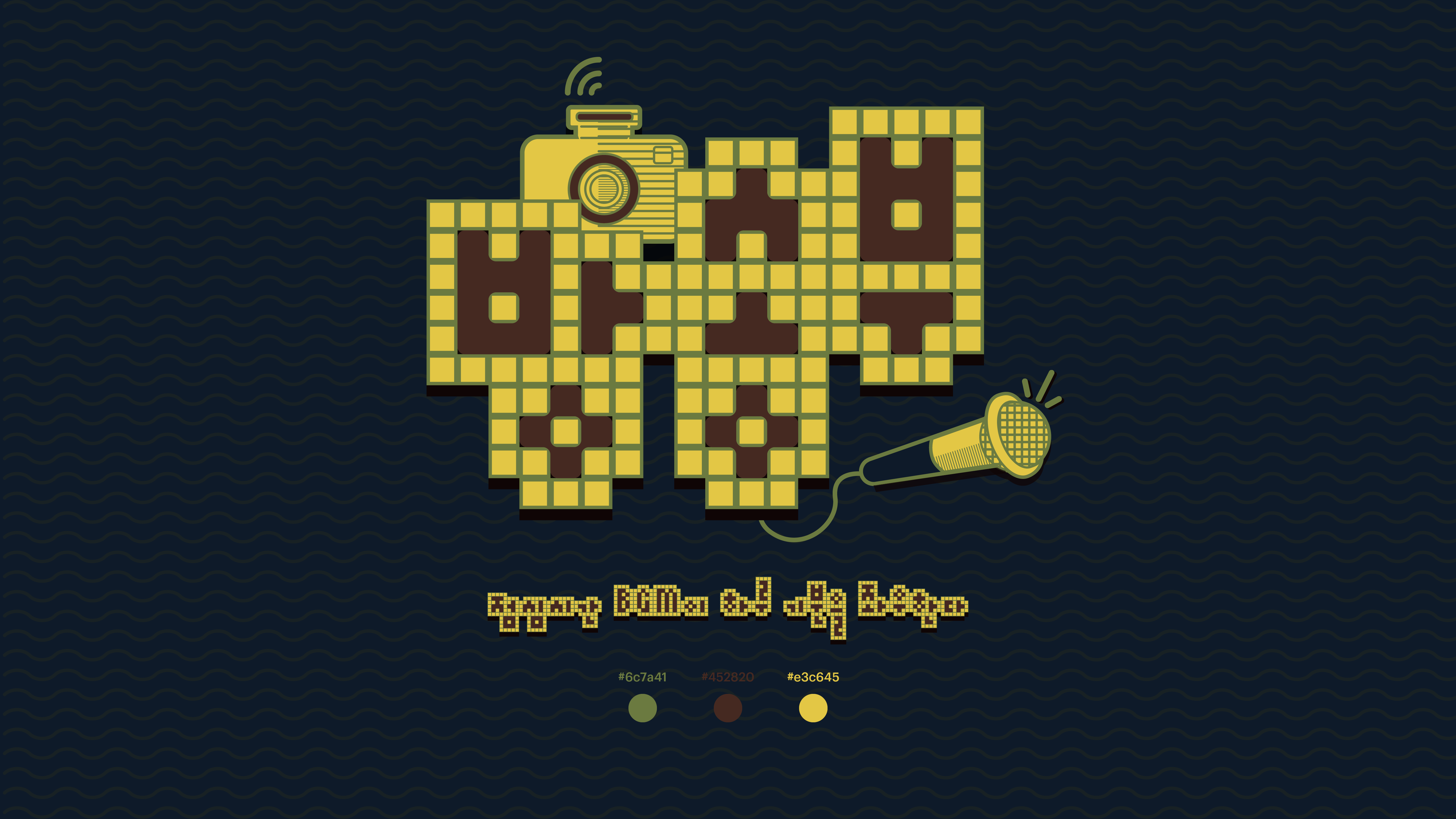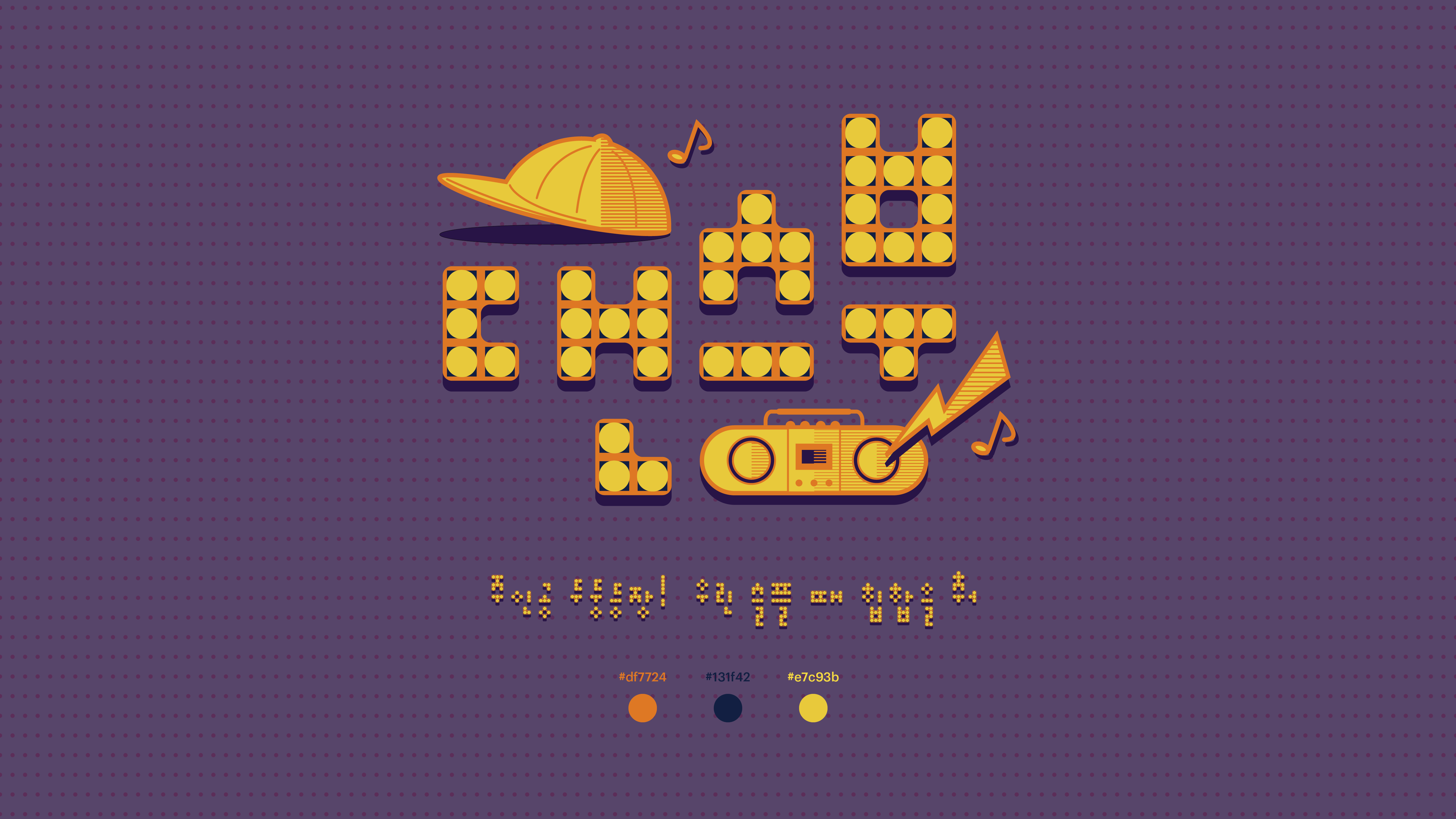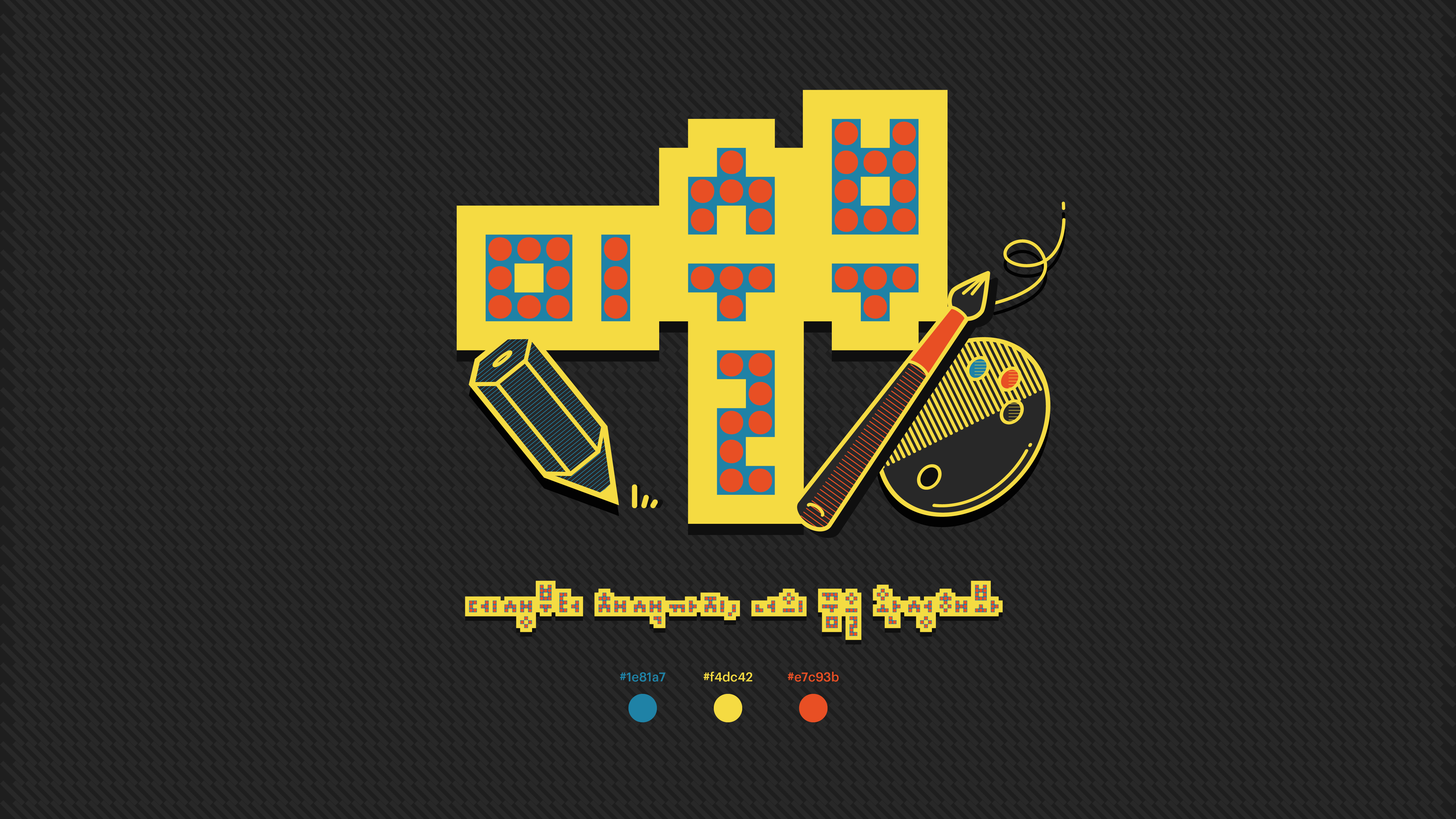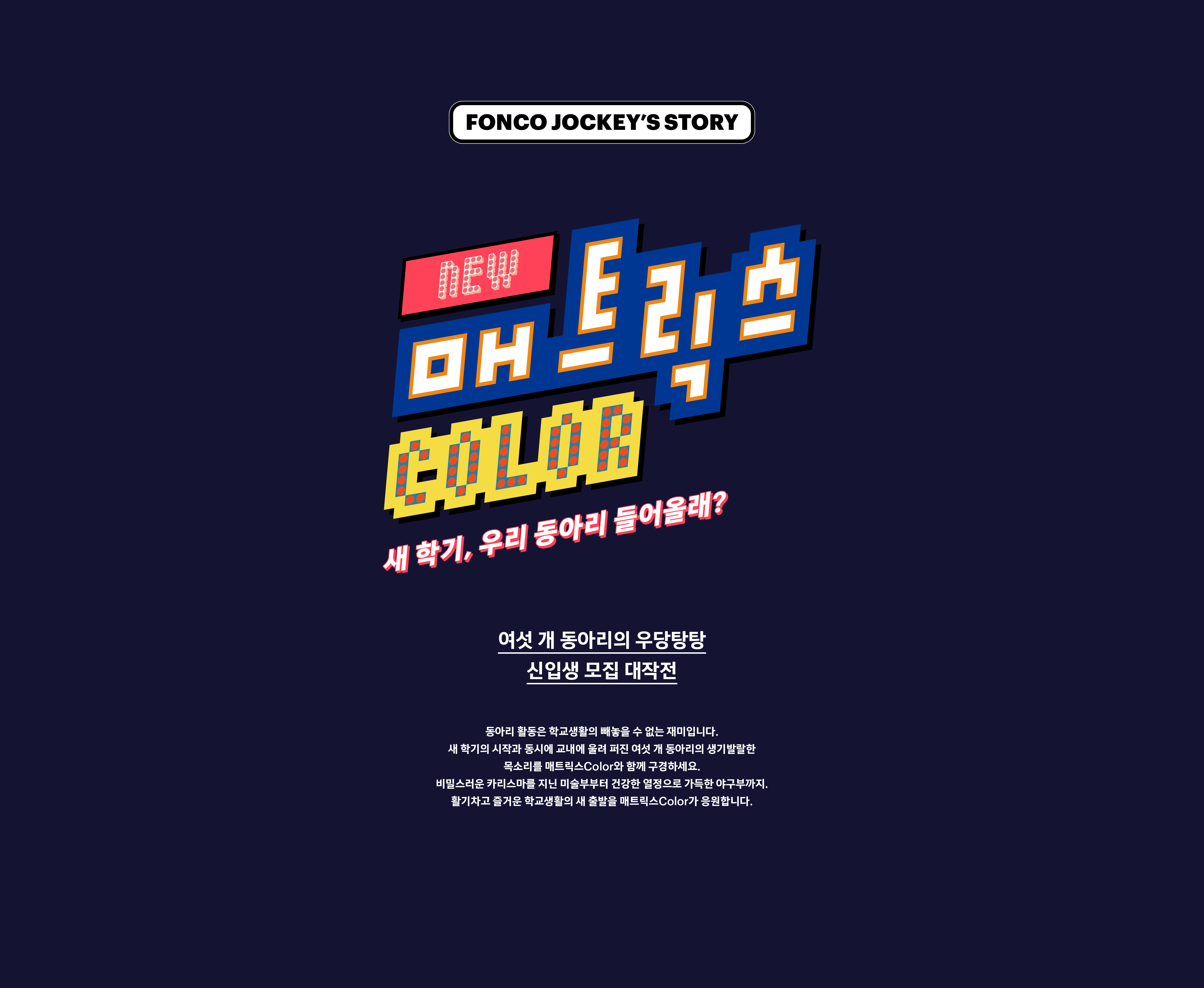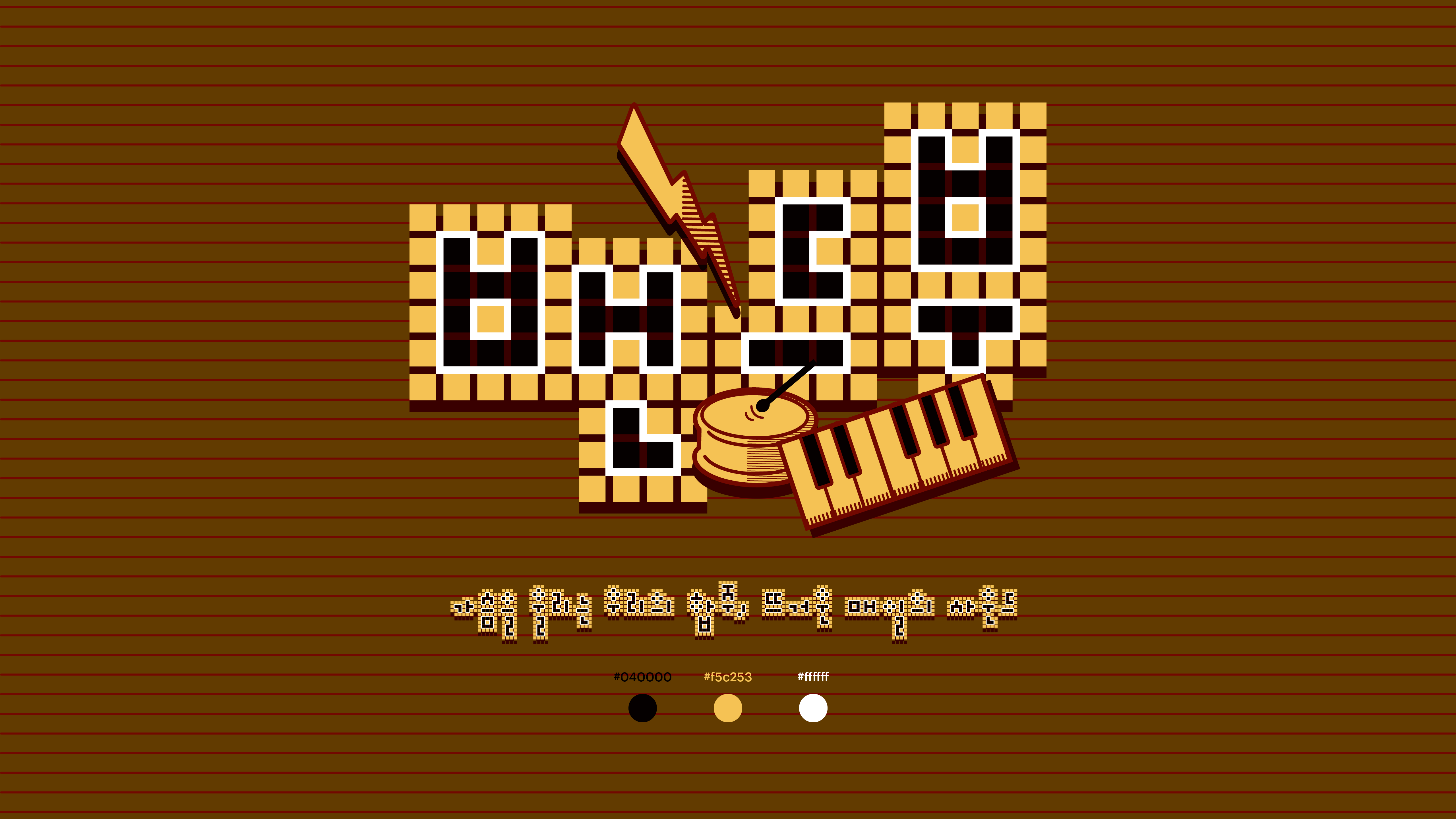
매트릭스 Color
Yoon 매트릭스 Color
동아리 활동은 학교생활의 빼놓을 수 없는 재미입니다. 새 학기의 시작과 동시에 교내에 울려 퍼진 여섯 개 동아리의 생기발랄한 목소리를 매트릭스COLOR와 함께 구경하세요. 비밀스러운 카리스마를 지닌 미술부부터 건강한 열정으로 가득한 야구부까지. 활기차고 즐거운 학교생활의 새 출발을 매트릭스COLOR가 응원합니다.